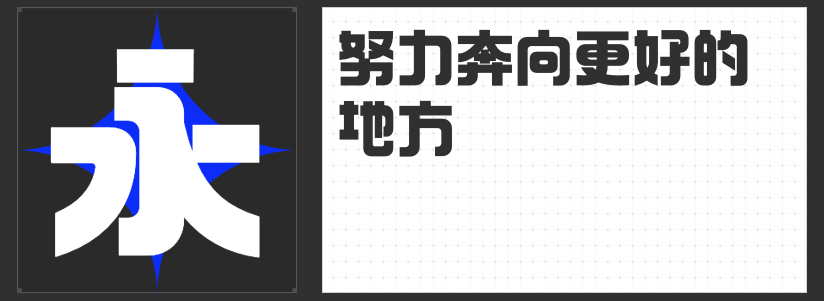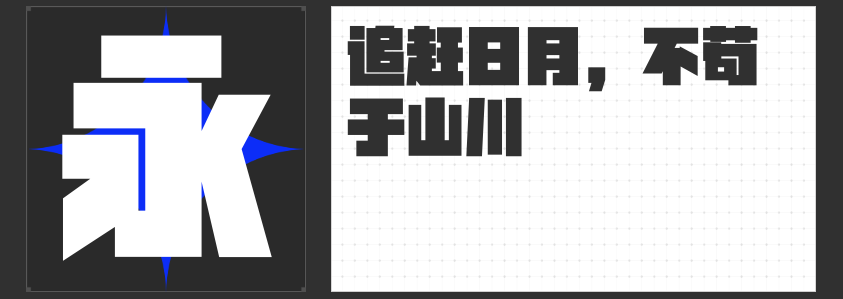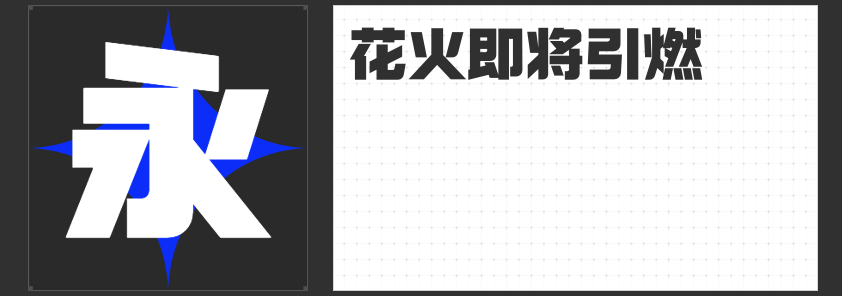
超黑视界|四款灰度超黑创意黑体,定义设计的力量美学
在追求视觉张力的设计领域,灰度超黑字体正以颠覆传统的姿态重塑信息层级。今天推荐的这四款创意黑体,以极致的墨色浓度与突破性的几何结构,为设计师提供更具表现力的视觉语言,尤其适合需要瞬间抓睛的场景。
一、励字勇敢黑简 超黑
这款字体以「零干扰阅读」为核心理念,去除一切装饰性衬线,将笔画压缩至极限宽度。粗壮的笔身搭配钝角处理的撇捺,在保持横竖均匀的节奏中注入工业感力量。其超黑灰度能形成强烈的图底对比,适用于新闻导语、品牌主标、警示标识等场景,即使在小字号下依然保持清晰辨识度。
二、造字侠地铁修悦体 超级粗
源自东京地铁的暖心故事,这款字体将佐藤修悦的胶带拼贴艺术转化为数字形态。方正的骨架被几何切口分割,人工拼贴的不规则性被刻意保留,形成动态重心与呼吸式留白。特别适用于潮流海报、展览标题、文创衍生品设计,其「未完成」的手工质感能瞬间拉近观者距离。
三、励字开拓者简 超特黑
这款字体堪称「互联网梗文化」的视觉载体,不仅完整收录又、双、叒、叕等叠字奇观,更以去钩笔处理强化镜像效果。直线笔画的绝对统治与内部空间的几何分割,构建出未来感十足的视觉秩序,尤其适合科技产品发布、电竞海报、社交媒体话题标签等场景。
四、励字暴风简 超级黑
打破传统黑体「横平竖直」的桎梏,这款字体将笔画解构为梯形单元。横竖笔画的非对称分布制造视觉张力,而刻意保留的「印刷误差」质感,则让字体在工整中透出原始的手工温度。适用于先锋艺术展览、实验戏剧海报、独立音乐专辑封面等需要突破常规的设计领域。
这四款超黑字体如同视觉的武器库——有的以绝对力量震撼眼球,有的用解构主义制造对话,有的为网络文化赋予形态,有的以拓扑变形挑战认知。它们共同证明:在注意力稀缺的时代,灰度超黑不仅是信息传递工具,更是情绪引爆器。下次设计需要「一眼定胜负」时,不妨让这些字体成为你的秘密武器。